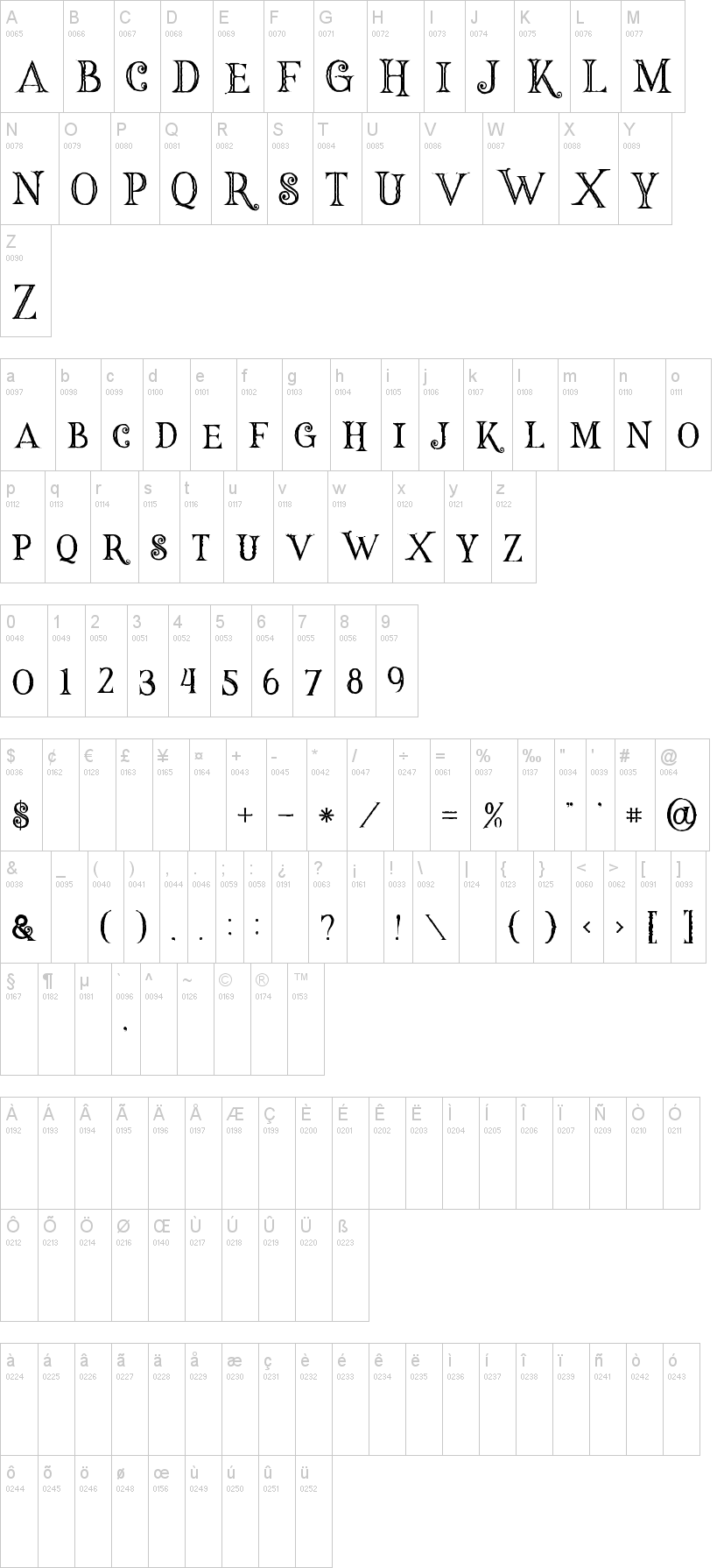
Halloween 字体是一种特殊的字体,通常用于万圣节相关的设计和文档中。它通常具有骷髅头、吸血鬼、巫婆、幽灵等与恐怖、神秘和幽暗气氛有关的符号和图案。因此,这种字体的风格通常比较独特,有时甚至颇具艺术感和创意性。 Halloween 字体可以用于万圣节相关的海报、传单、名片、T恤、装饰品等设计中,以营造节日气氛。同时,它也可以用于万圣节相关的卡片、邮件、文档等文字内容中,以增强文字的氛围感和可读性。 总之,Halloween 字体是一种非常适合在万圣节期间使用的特殊字体,通过它的使用,可以为你的设计和文档增添一份神秘、幽暗和有趣的气息。内容介绍
Hallowen是一款非常不错的手写艺术字体,具有很好的视觉感,适合于文化类的宣传设计、商业类品牌的广告和产品包装设计以及个性化文字排版等较多场景。